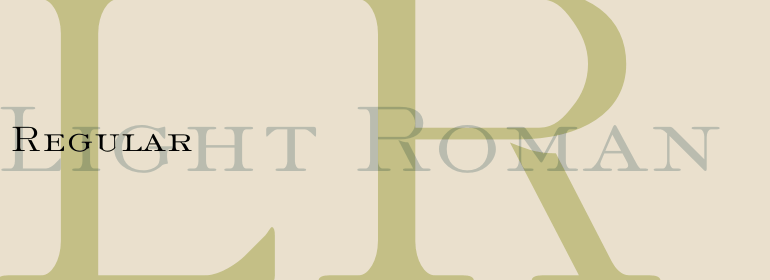
Light Roman™
Light Roman™,这款字体结构工整、笔画清晰,兼顾美观与易读性,适用于标题、正文、海报、包装、LOGO 等多种场景。字形优雅稳定,风格百搭耐看,适配日常排版与创意设计,让文字呈现更舒适、更具质感。Light Roman™一笔一画,皆是细节,以均衡的比例、流畅的线条打造舒适视觉体验,字形端正大气,风格简约现代。无论是商业设计、品牌宣传还是日常排版,都能轻松驾驭,让文字更有格调与力量。Light Roman™字体下载。
字体品牌: Monotype 设计师:Monotype Design Studio 字体分类:衬线体 字体属性:外文 字符集:Unicode 发布时间: 2018
Light Roman is an engraver, all-capitals font for invitations and stationery. The Light Roman font has strong contrast between thin and thick strokes.